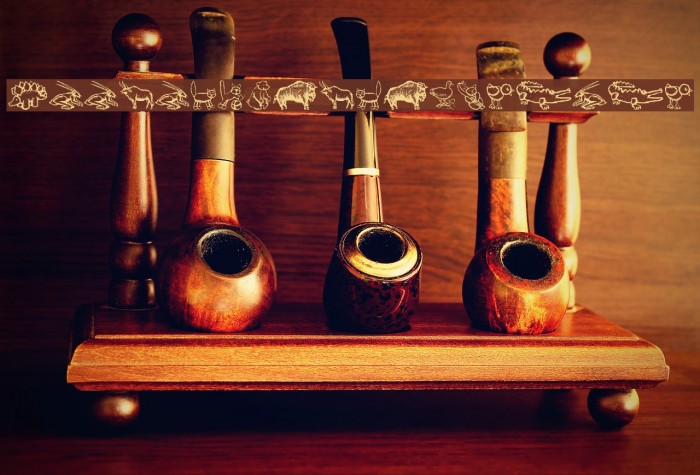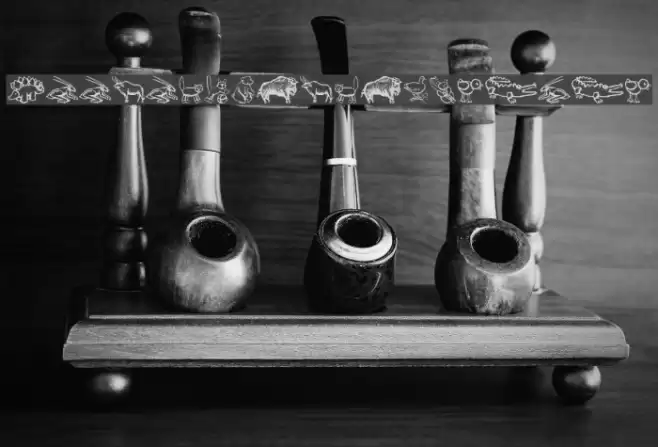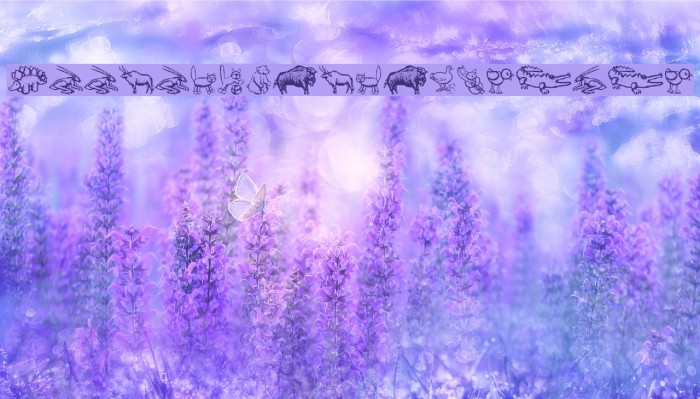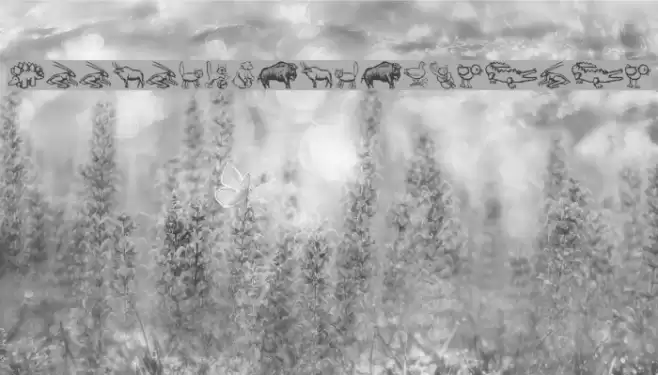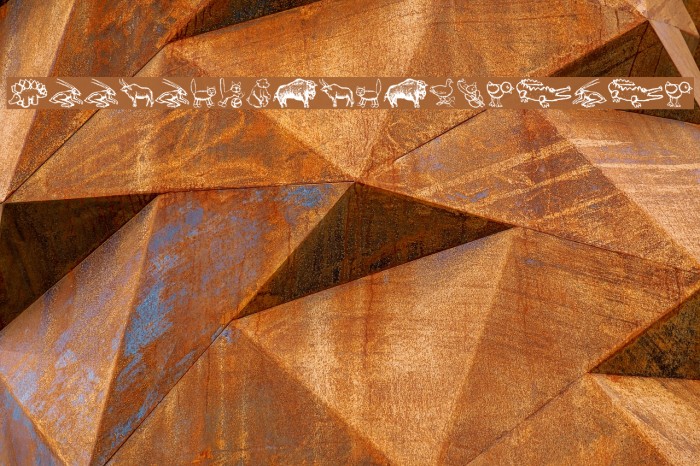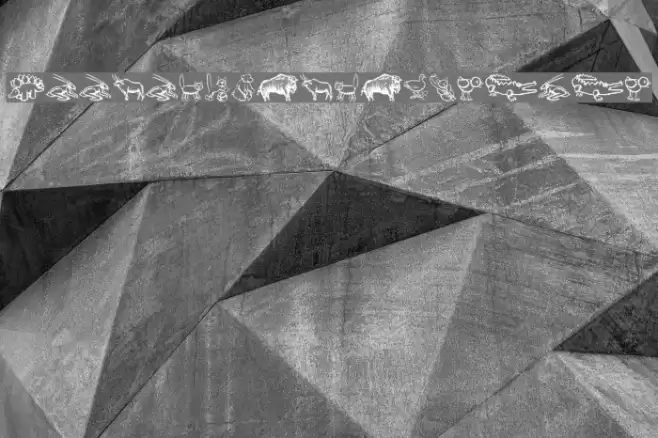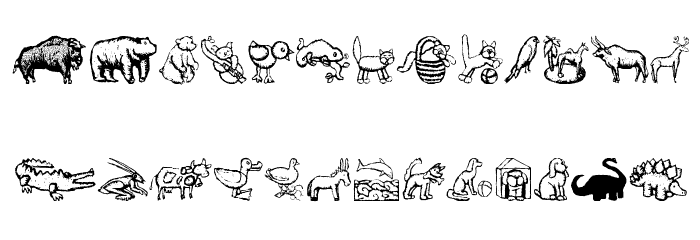
ZoologicalGardenOne Font
| Style général | Decorative, Whimsical, Playful |
| Cas d'utilisation | Logos, Headlines, Posters, Children’s materials |
| Projets proposés | Children’s books, educational materials, zoo event posters, party invitations, playful branding. |